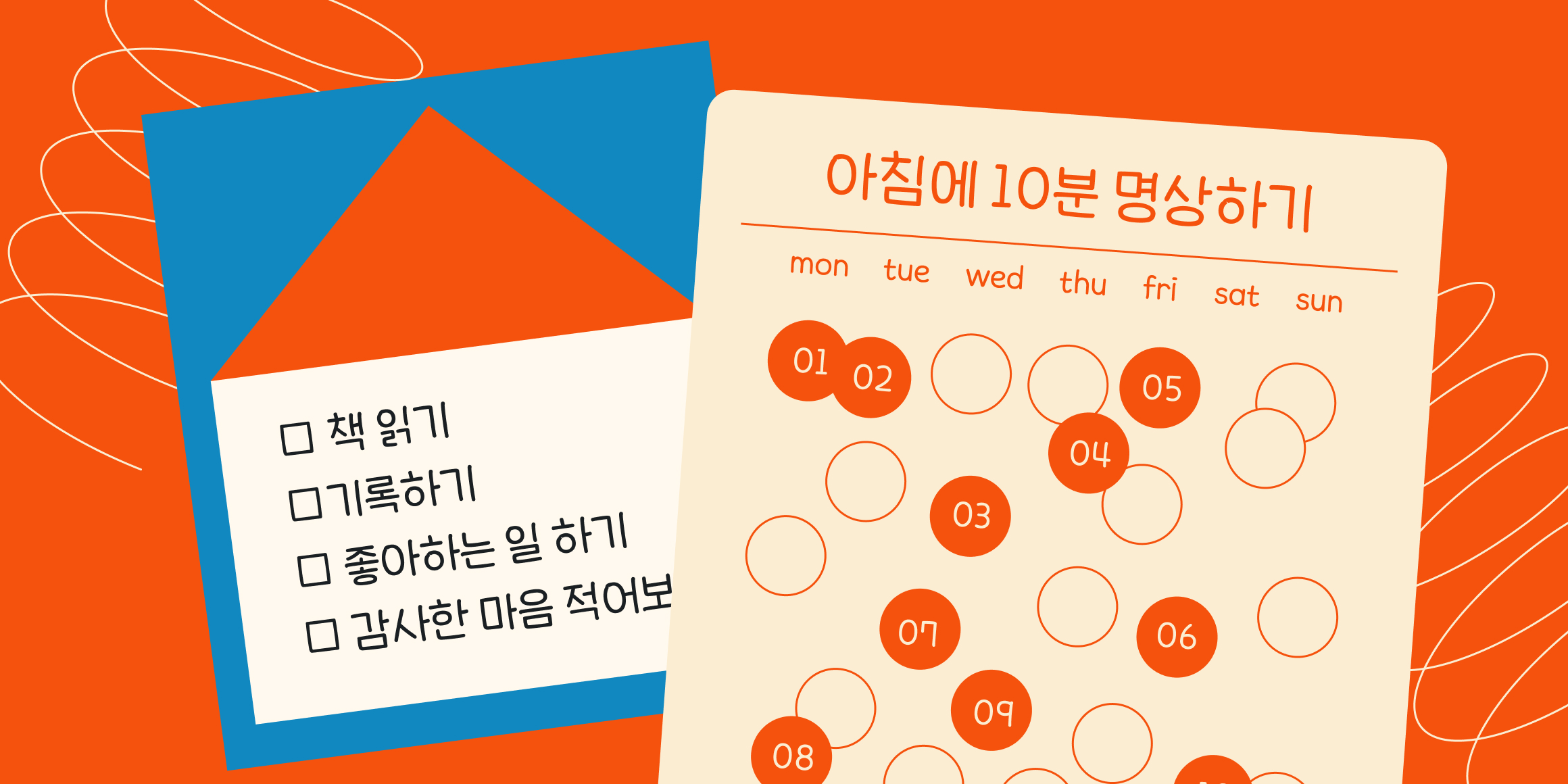
HG굴린꼬딕씨
Hangulssi
HG굴린꼬딕씨는 HG꼬딕씨의 외곽선을 곡선적으로 처리한 제목용 고딕 서체입니다. 탄탄한 네모꼴 제목용 글꼴의 기본 형태 위에서 획의 끝과 꺾임에 최적의 Round 값을 적용하여 굵기에 어울리는 표현을 최우선으로 디자인되었습니다. 그로 인해 보다 부드럽고 귀여운 인상을 가진 새로운 제목용 서체가 제작되었습니다.
6가지 웨이트의 풍부한 패밀리로 구성되어 있어 용도에 맞게 사용할 수 있으며, 2,350자의 한글 글립이 디자인되어 있습니다. 각 두께의 모든 글립이 같은 폭으로 이루어져 있기 때문에 디자인 작업을 할 때 Grid를 맞춰서 쉽게 활용할 수 있습니다. 영문 디자인은 한글과 혼용하여 사용할 때 한글의 어절 공간과 영문의 어절 공간의 균형을 주로 고려하여 글자의 폭을 정하고 그를 토대로 그려나갔습니다.